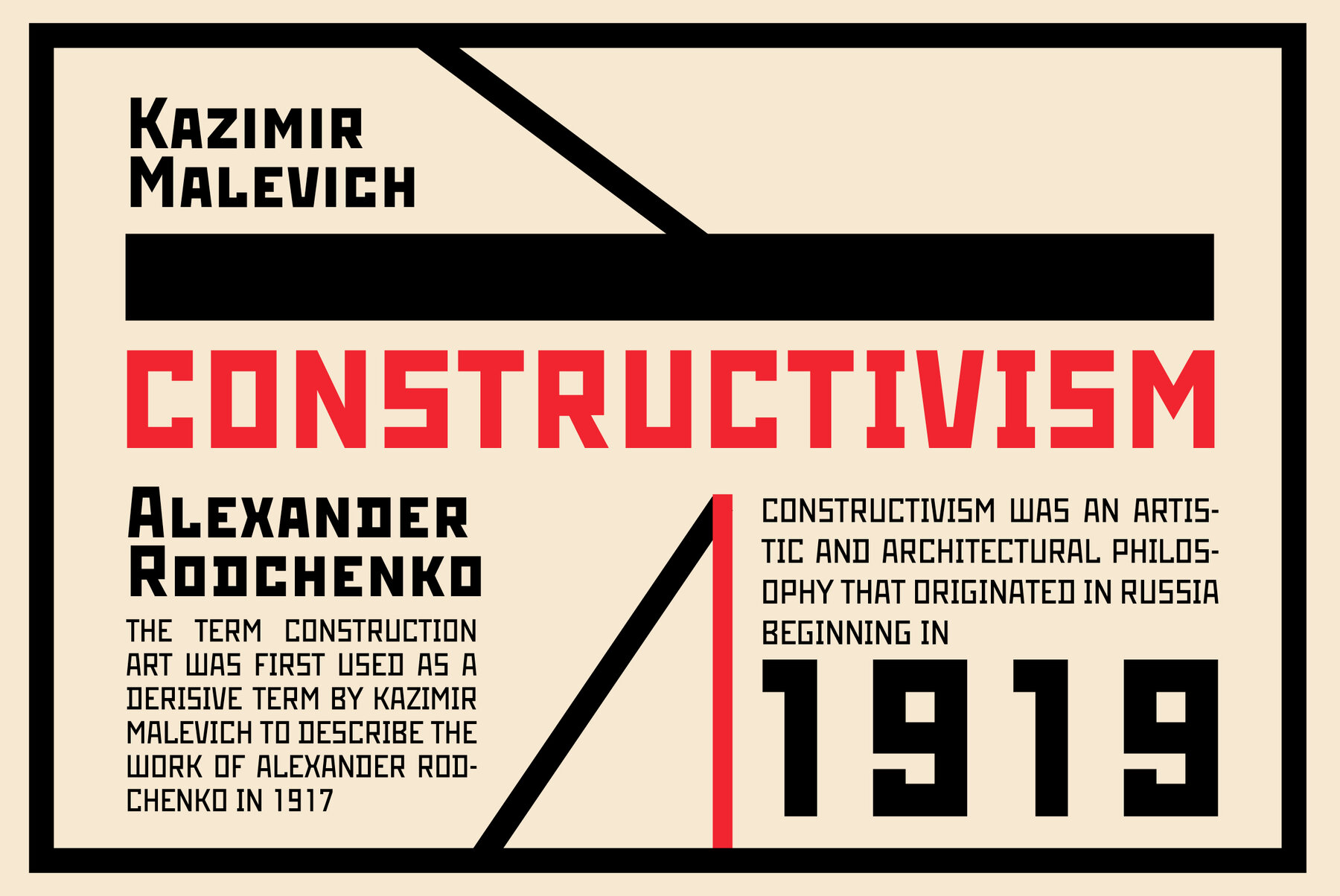
Пределы совершенства
Давно крутится в голове мысль записать свои ощущения от изменений фактуры, гладкости, идеальности контура в леттеринге на камне, в каллиграфии и шрифте.
Эта мысль возникла, когда мы в Кембридже рассматривали доски, награвированные мастерской Кардозо-Киндерсли, идеальные с технической точки зрения. Подумалось, что какие-то 20–30 лет назад они выглядели просто невероятно, неужели можно добиться такого совершенства, такой точности линии! А сейчас мало кто осознаёт в полной мере, что это сделано вручную (настолько гладок и безупречен результат), и мы не можем восхититься работой так, как восхищались совсем недавно. До чего неожиданно, должно быть, для многих повернулась история, и как изменилось восприятие! Могли бы предсказать сами мастера, что вот так вдруг вместе с развитием техники гладкость контура перестанет восприниматься однозначно как идеал?
Памятная доска физику Джосефу Томсону (1856–1940), обнаружившему электрон.
Гладкость и блестящее совершенство контура ручной работы сильно потеряли свою ценность с появлением цифровых инструментов (например, в гравировании на камне). Появилась возможность (отчасти иллюзорная) для непрофессионала добиваться результата, который раньше требовал большого опыта. В общем и целом за «ровность и гладкость» теперь отвечает автоматизированный инструмент. Человеческая рука, наоборот, становится носителем не столько мастерства и точности, сколько эмоциональности, спонтанности — по крайней мере, в ожиданиях зрителя.
Система координат перевернулась. Те вещи, в которых точность ручной работы достигла какого-то сверхъестественного качества, вдруг стали «проваливаться» в нашем восприятии и в нашей оценке. Компьютер делает эту работу быстрее и дешевле, присмотреться мы не всегда успеваем, а прикосновение руки в идеальной ручной работе почти не заметно.
Научить компьютер делать так же, как это делает живой мастер, — дико азартная игра… Получается, что совершенствование нового инструмента во многом интереснее, чем результат: высокое качество уже достигнуто, теперь интересно делать то же самое, но другим способом (скорость и стоимость оставлю за рамками).
Предельной точности в каллиграфии добивался Герман Цапф (1918–2015), который обладал удивительным чувством идеальной формы, невиданной раньше, и доводил каллиграфические надписи до совершенства, ретушируя контур / Index Graphik
Гладкость контура — как гладкость дороги. По ухабам не проедешь, а по ровной и покрытой наледью дороге скользишь и летишь вперед. Сверхгладкий контур буквы (да и другого объекта) задаёт глазу высокую скорость (но не чтения, а скорее рассматривания) — и взгляд не задерживается. Недавно мы обсуждали с друзьями-каллиграфами, почему часто прекраснейшие каллиграфические листы не читают, хотя автор придаёт тексту большое значение.
Возможно именно по той причине, что слишком виртуозны и идеальны линии, и взгляд пробегает по ним без труда и очень быстро, наслаждается лёгкостью движения и летит дальше.
Работы Рейчел Яллоп — предел идеальности контура, по которому глаз скользит и не может остановиться.
Раньше шероховатость бумаги и растискивание краски были неизбежными, а теперь в каких-то случаях могут быть желанными. Конструктивистские рисунки, чертежи, шрифты на современной бумаге выглядят безжизненно — в оригинале (меньше века назад!) они смягчены и одушевлены осязаемостью материалов. Те же формы, но в «идеальном» контуре и без выраженной фактуры бумаги теряют коммуникативность, взгляд проскакивает по ним.
Особенно сложен в «переводе» на современные материалы «палочный шрифт» — именно из-за того, что предельно прост и геометричен.
Попадая в мир, где геометрия стала слишком точной (извините за такой оборот), такой шрифт может стать неинтересным и примитивным. В эпоху конструктивизма сама геометрия была рукотворной, рисованной, края геометрических фигур дышали рукотворной неидеальностью, поэтому современные цифровые интерпретации конструктивистских шрифтов из-за своей чрезмерной гладкости и точности сильно проигрывают тем рисункам букв, которые предложили конструктивисты.
Моноширинный палочный шрифт Б. Эмме из его книги «Шрифт: Элементарное руководство для практического использования в клубе, школе, пионер-отряде и т. д.» (Ленинград, Гос. изд. изобразительных искусств, 1931)
/ А. Домбровский, В. Кричевский. Два шрифта одной революции. М.: Шрифт и Мастерская, 2014.
Кажется, глянец и фактурность в графической культуре в целом в каждый период сохраняют примерно одинаковые пропорции, просто перемещаясь из одной сферы в другую, меняясь местами — от каллиграфии к наборному шрифту, в рисованные надписи и обратно.
Если точность и глянец восторжествовали в шрифтовом дизайне — в каллиграфии усилится фактурность, и наоборот, когда каллиграфия была точнее печатного контура, шрифт боролся, но не пробивался к точности воспроизведения. Только пуансонист, возможно, грезил идеальным контуром, который на листе станет таким же идеальным, как и в пуансоне, который он вырезает.
Какой простор для дискуссий и выбора даёт эта разница между ренессансным пуансоном и оттиском для дизайнеров, которые восстанавливают классические шрифты: брать за образец пуансоны, или оттиск, или что-то среднее? Какая форма буквы была желанной, каким было намерение пуансониста? Какую поправку на неровность печати, густоту краски, рельефность бумаги он закладывал в дизайн шрифта? И что было случайностью или неизбежностью?